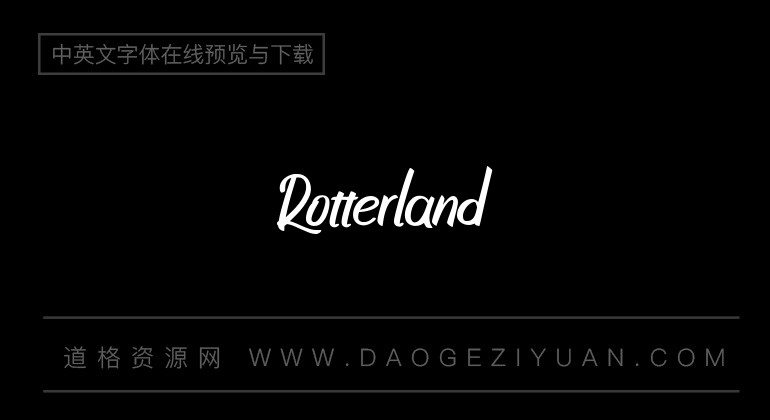
Rotterland
? Rotterland字体是一款由荷兰设计师Rutger Paulusse设计的现代简约复古字体。该字体有着粗犷的轮廓、细腻的细节和温暖的气息,适合用于品牌标识、海报、书籍封面、网站标题等应用场景。Rotterland字体包含英文字母、数字、标点符号,以及中文汉字。
Rotterland是一款非常不错的手写艺术字体,具有很好的视觉感,适合于文化类的宣传设计、商业类品牌的广告和产品包装设计以及个性化文字排版等较多场景。